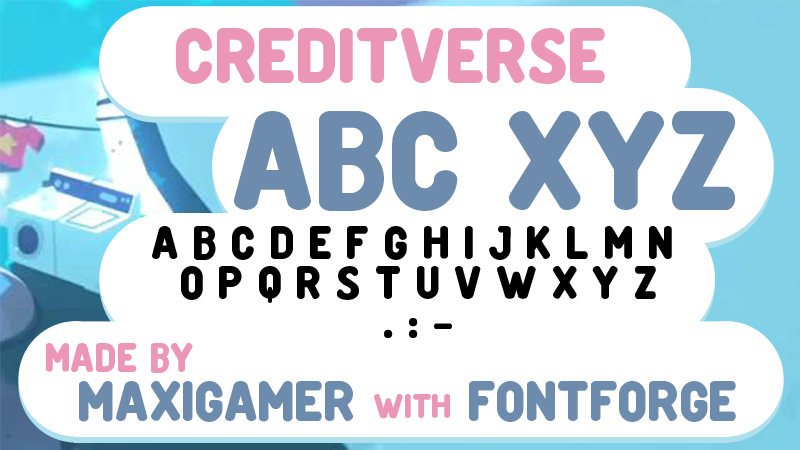
Creditverse font family
A fonte Creditverse foi projetada para imitar a utilização na legenda final do famoso programa animado Steven Universe™. Inspirada no universo criado pelo mestre Hamilton, essa elegante e moderna fonte serifless transmite uma sensação de confiança e simplicidade, perfeita para qualquer aplicativo ou projeto digital que valorize estética minimalista e alta qualidade. Seja você um designer gráfico ou um desenvolvedor de sites, Creditverse oferece o tom preciso e alegre necessário para destacar seu trabalho em cada detalhe. Uma vez mais, este é apenas um exemplo da versatilidade desta fonte que combina graça moderna com uma conexão direta ao universo de Steven Universe™.